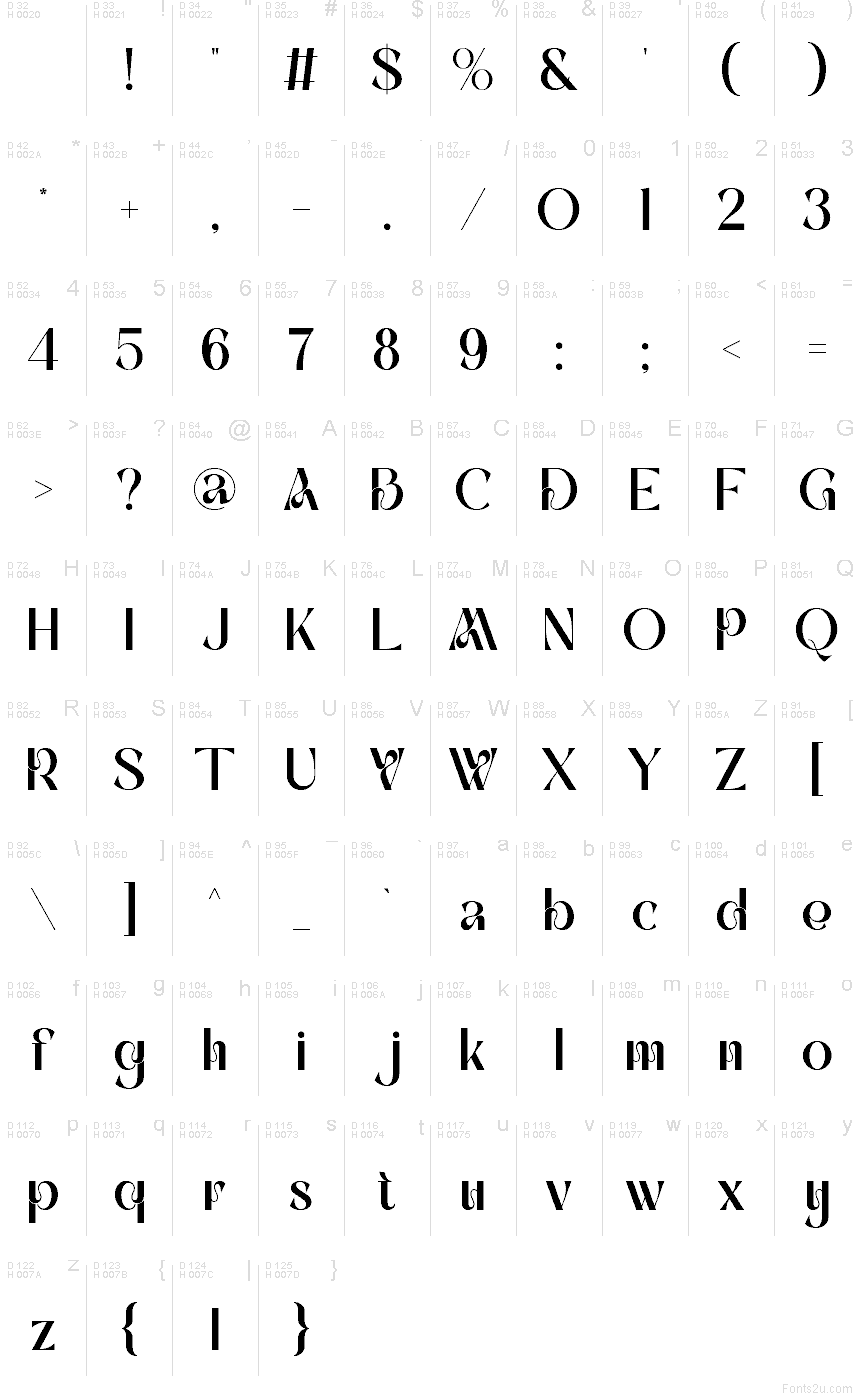
Eravo od Ermedia Studio to darmowy krój typu display w stylu retro, charakteryzujący się wysokim kontrastem i modną sylwetką. Szerokie, rzeźbiarskie krzywe spotykają się z niezwykle cienkimi liniami, a ostre cięcia i nieoczekiwane, haczykowate detale nadają literom dramatycznego sznytu rodem z edytoriali lat 70., przy zachowaniu wyrafinowanej elegancji.
Wykorzystaj ten darmowy font w nagłówkach magazynów o modzie, opakowaniach perfum, okładkach albumów, tytułach książek artystycznych oraz plakatach kampanii kulturalnych. Połączenie zamaszystych krzywych z ostrymi, przypominającymi ostrza łączeniami sprawdza się szczególnie dobrze w krótkich nagłówkach, gdzie odpowiednio dobrany odstęp pozwala wyeksponować najbardziej ekscentryczne kształty w kompozycji.